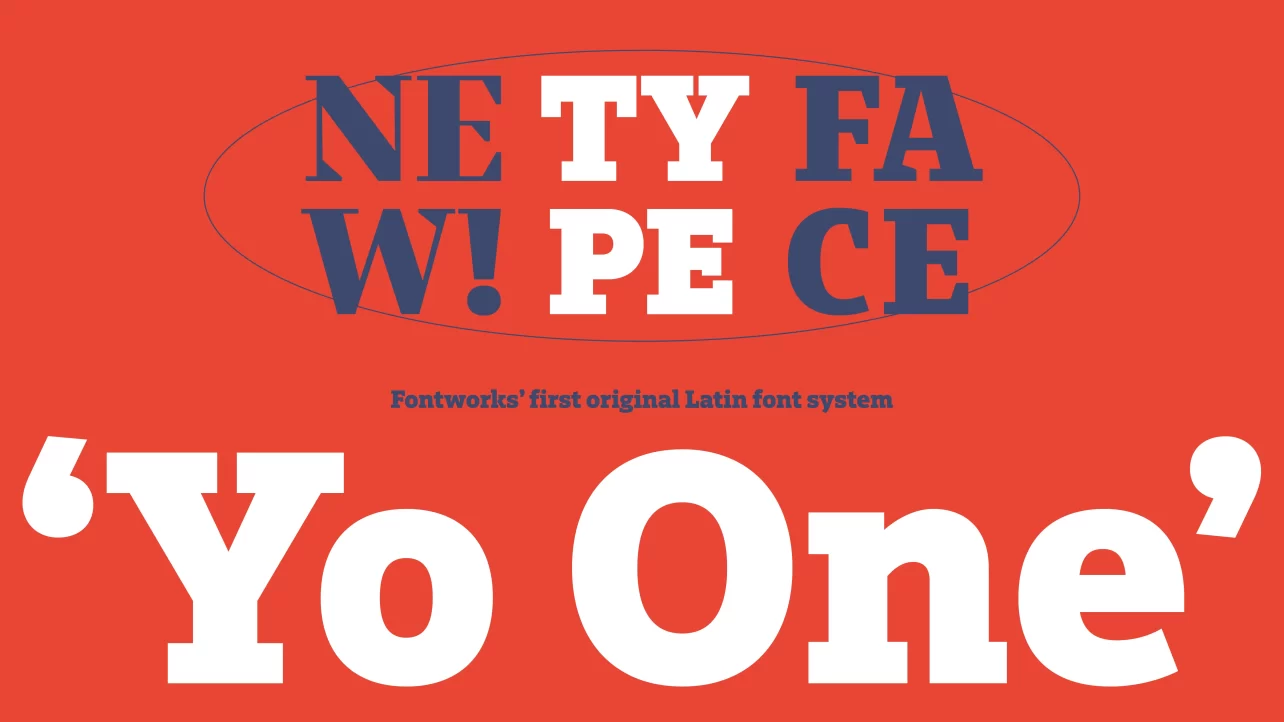
新書体「Yo One」について
フォントワークス書体デザインディレクター ヨアヒム・ミュラー゠ランセイが制作したYo Oneは、欧文書体が持つさまざまなバリエーションを複数の軸で体系化したフォントシステムであり、156フォントを有するスーパーファミリーです。大きく分けると6つのファミリーで構成されています。まず「セリフ・サンセリフ」の2スタイルに分かれ、それぞれに書体の特徴を表す「リニア・セミ・コントラスト」の3フレーバーがあります。
各ファミリーが13ウエイトで展開され、それぞれにローマン体とイタリック体の2アングルを用意しています。6ファミリー(2スタイル × 3フレーバー)× 26サブファミリー(13ウエイト × 2アングル) = 156フォントこれらのバリエーションの中から、フレキシブルにフォントをご選択いただけます。
Yo Oneスーパーファミリーは、一つの字形から出発し、セリフの有無、コントランスの強弱など異なる特徴をもつ書体へ展開されていきます。統一されたルールで設計されたスーパーファミリーなので、セリフとサンセリフなど異なる特徴を持つフォントを組み合わせて使用しても調和を保つことができます。ブランディングなどで視覚的な統一性が必要なシーンにもおすすめの書体です。
美しさと実用性を極めた、ネオヒューマニスト書体
Yo Oneは、ぬくもりを感じる親しみやすさと、信頼性と実用性を兼ね備えた汎用性の高い書体です。現代的でクリーンかつ鮮明、あらゆるニーズに対応する書体としてデザインされました。全てのスタイルの基礎となっている骨格は「ネオヒューマニスト」です。欧文書体の歴史の中で、1950年台に急増したネオグロテスク・サンセリフに対して、より読みやすさを向上させたヒューマニスト・サンセリフが台頭してきました。これらはカリグラフィの手の動きを取り入れ、自然に書かれたようなストロークを再現しています。ネオヒューマニスト書体は、それがさらに発展したものです。
文字ごとの形状の違いが大きく、識別しやすくなっています。特徴的なのは「C」「e」「3」などに見られるオープンカウンター形状で、開口部を広く取ることにより、判別性や視認性が向上しました。
ポスターやパッケージ、Webデザインだけに限らず、各種デバイスへの組込み用フォントにもおすすめです。